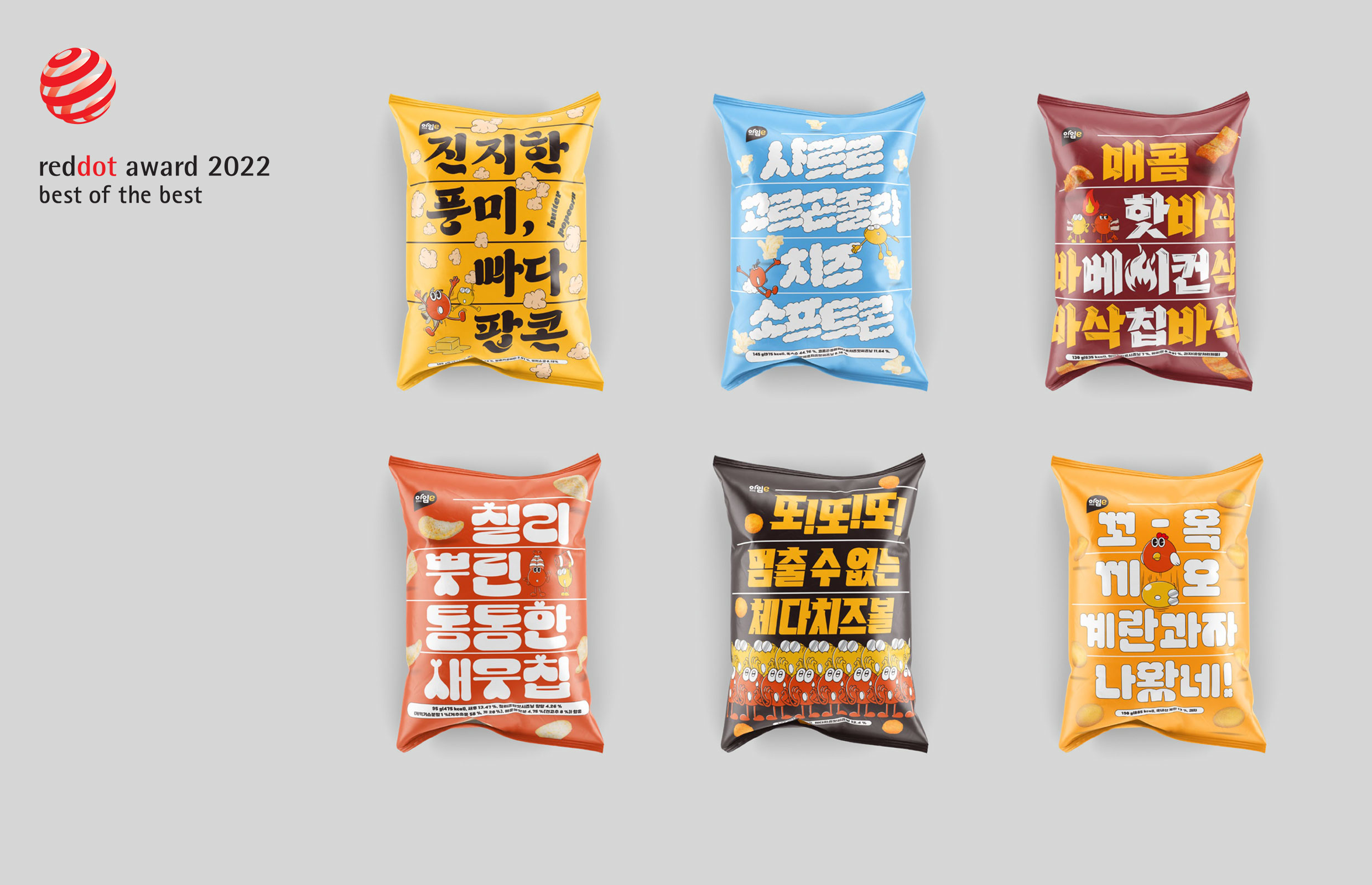
이마트24는 자체 개발상품(PL) 아임e 스낵 5종 패키지 디자인이 독일 레드닷 디자인 어워드 2022년 브랜드&커뮤니케이션 부문 본상을 수상했다고 5일 밝혔다.
레드닷 디자인 어워드는 1955년부터 독일에서 개최되는 국제적인 디자인 시상식이다. 미국 ID EA(International Design Excellence Awards),
독일 iF(International Forum) 디자인 어워드 와 함께 세계 3대 산업 디자인상으로 꼽힌다. 이마트24는 지난 7월 아임e 스낵 5종 포장 디자인을 바꿀 때 자체 개발한 개성 있는 타이포그래픽(서체)을 적용했다. ‘샤르르 고르곤졸라 치즈 소프트콘’ 같은 제품명을 그 상품의 맛이나 식감을 보여줄 수 있는 서체로 표현한 것이 특징이다.
이 제품 디자인은 레드닷 디자인 어워드 수상작 중 상위 1%에게 주어지는 '베스트 오브 베스트'에 선정됐다. 포장 디자인을 바꾼 후 8월 2일까지 아임e 스낵 5종 매출은 기존 패키지 상품 대비 1.3배 높게 나타났다.